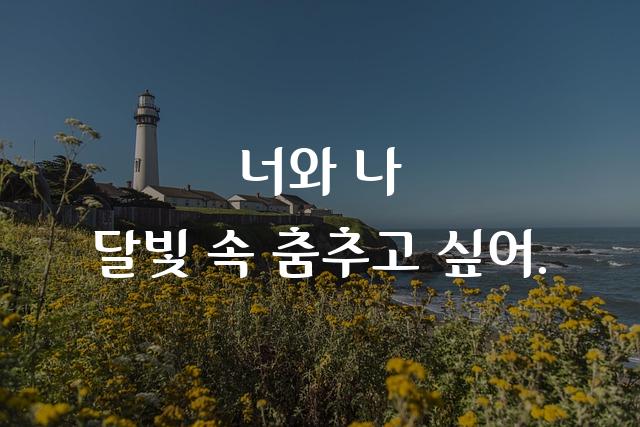
달서힐링체는 부드럽고 둥근 고딕 스타일의 한국어 폰트로, 사용자에게 편안함과 따뜻한 감성을 전달합니다. 이 폰트는 감성적인 디자인과 기술적인 세련미를 겸비하였습니다.
달서힐링체은(는)
기본 고딕, 둥근 스타일, 감성적인, 부드러움, 복실복실 계열의 생김새를 가지고 있으며
어린이 책, 인사말 카드, 카페 메뉴 등에서 자주 활용되며, 효과적인 메시지 전달에 적합합니다.
이 폰트는 음식/식음료, 라이프스타일, 유아/가족 분야에 잘 어울리며,
따뜻한, 친근한, 편안한 느낌을 담고 있는 것이 특징입니다.